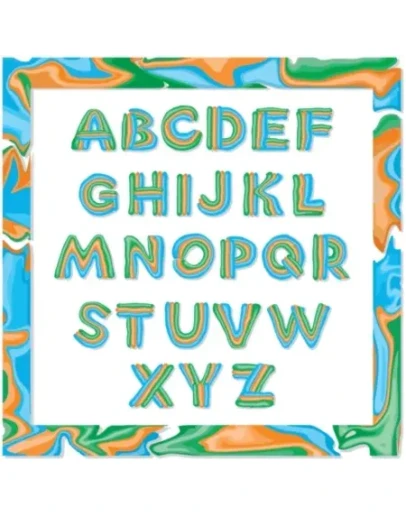
Латинские буквы, все буквы английского алфавита, векторный декоративный шрифт для заголовков и оформления. Буквы, как будто вылепленные из разноцветного пластилина. Ссылка на прямое скачивание архива. В архиве векторные файлы eps и cdr, а также растровые файлы высокого разрешения: jpg и png с прозрачным фоном.
Векторный декоративный шрифт, буквы из пластилина